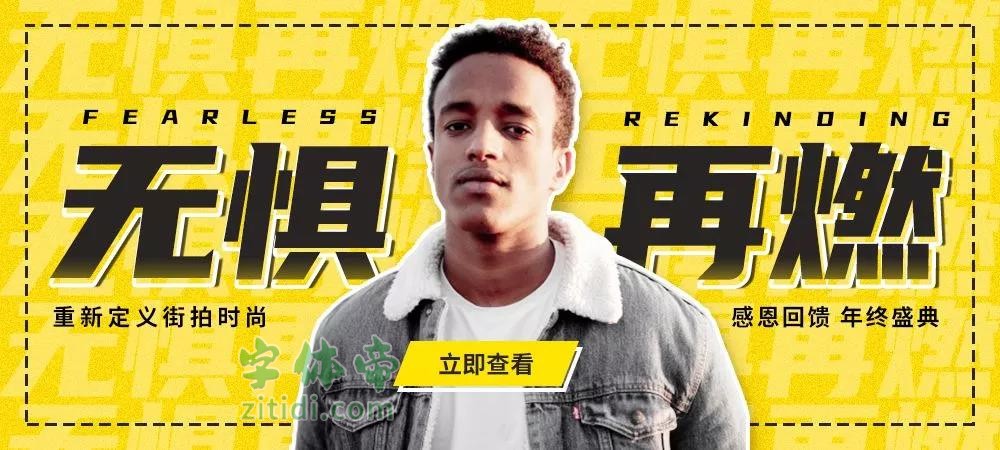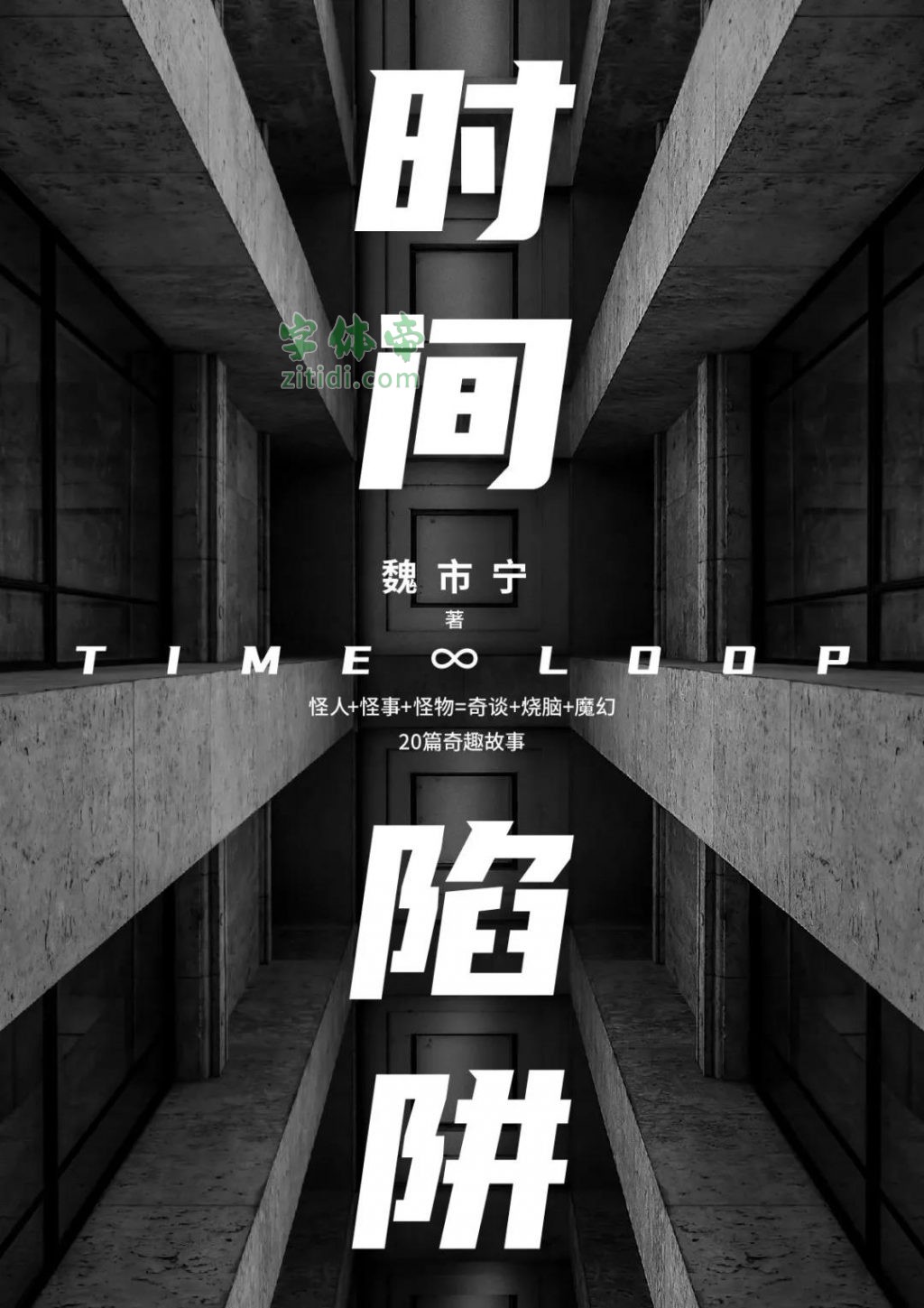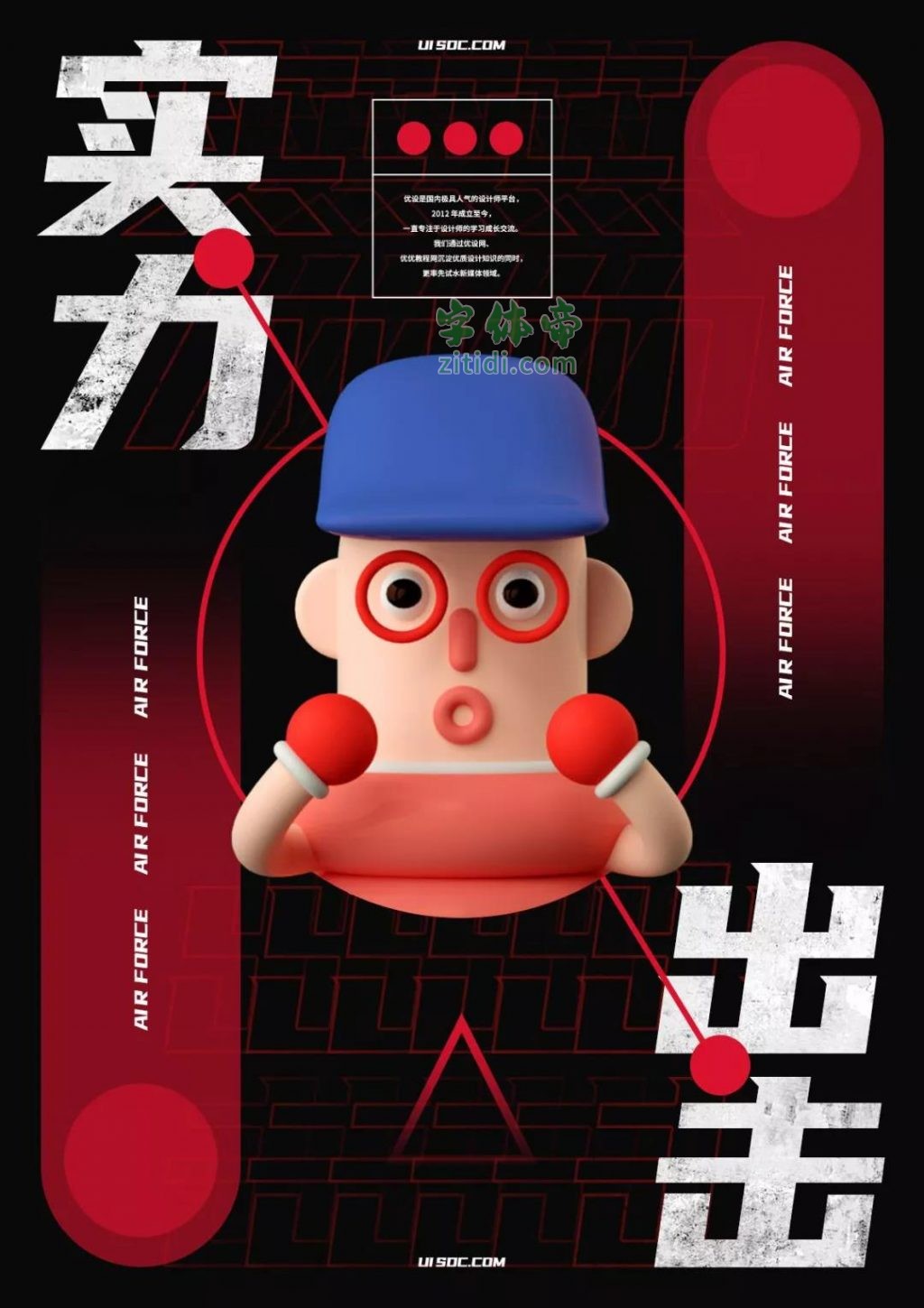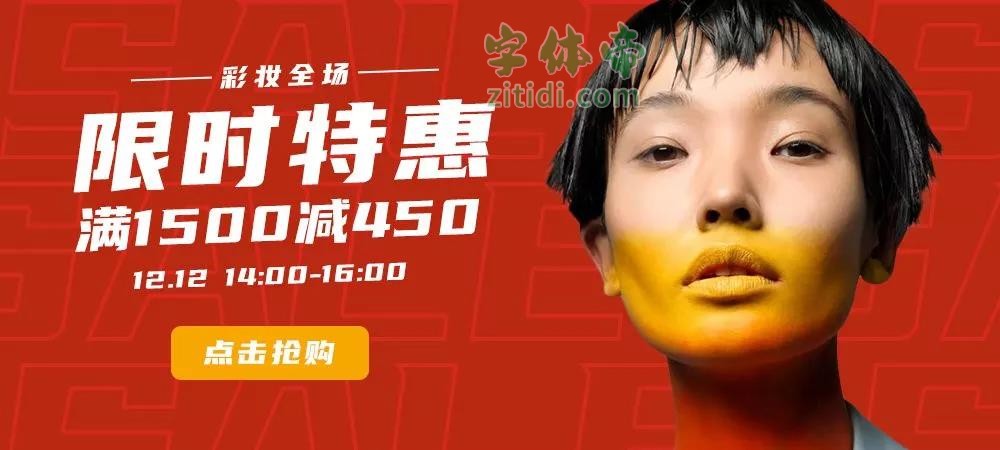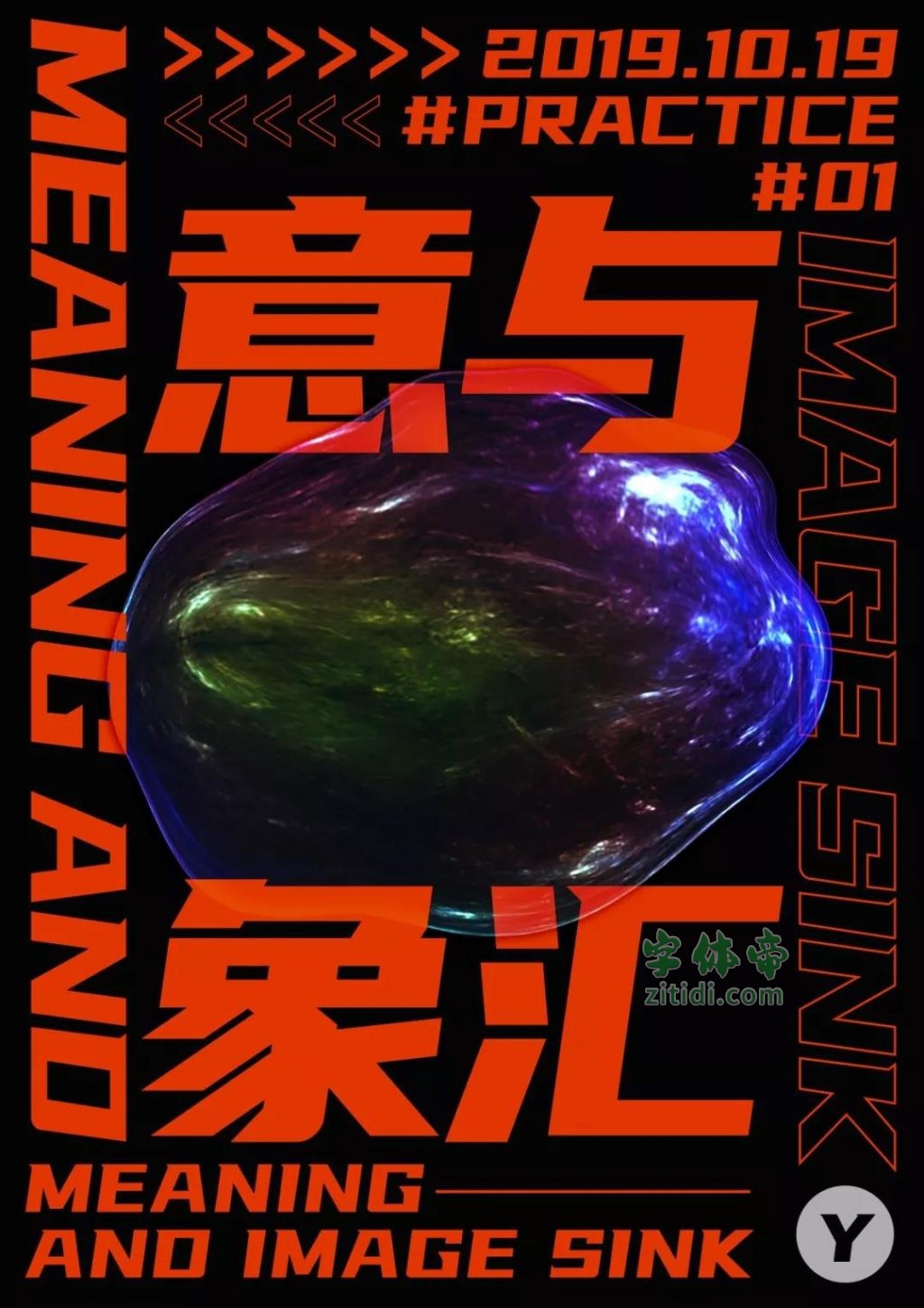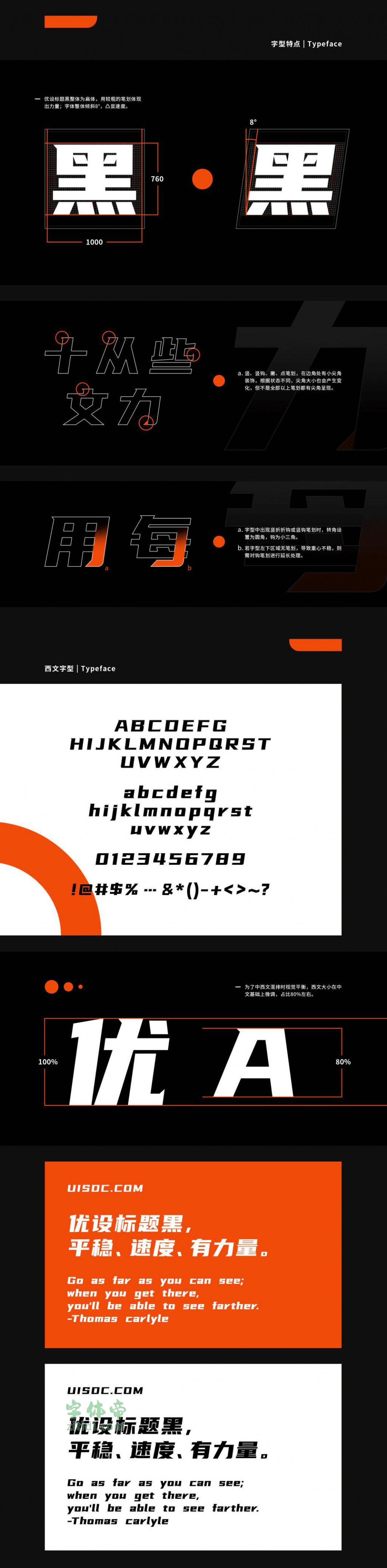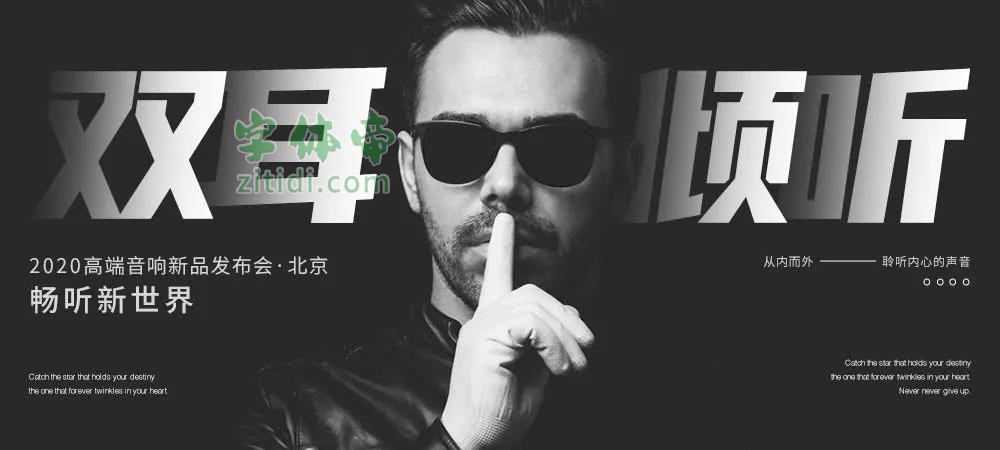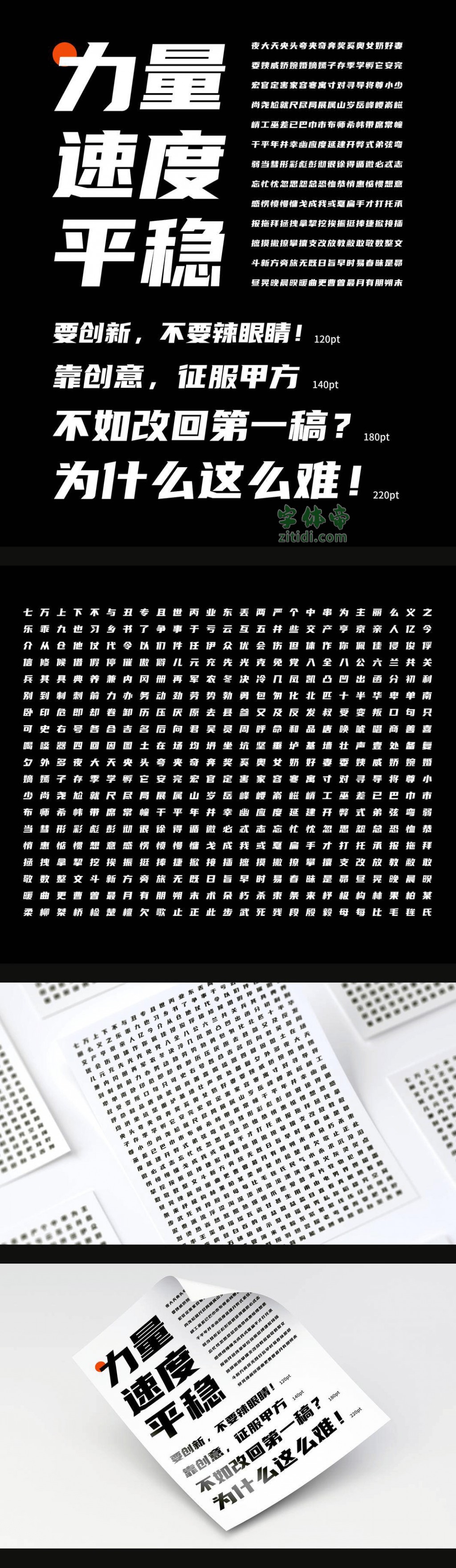
优设标题黑的设计思路来源于对目前市面上宣传物料标题用字的观察。我们发现越来越多的广告标题字体会使用这类倾斜的、粗壮的黑体字。但目前市面上这类中文字库少之又少,多数还是需要设计师自行设计。所以在优设8周年之际,为了感谢粉丝们的一路支持,优设联合字由平台共同特制这款免费可商用字体为行业献礼。
在最初有了要制作一款免费商用字体的想法时,正好遇到字由的朋友,我们一拍即合,达成了联合发布优设免费字体的共识。为了保证字体顺利快速的发布,优设邀请字由联合参与并对字体的质量把关,在优设制定完 300 多个基础字型、字母及符号的创意与规范后,字由接手继续从字库角度出发,整体完善优化字型,完成了6000多个字型的制作,并用了大量时间来进行产品化和字体细节方面的优化。
历经 100 多天,不断推翻和调整细节后,这款包括 6763 个汉字和字符的「优设标题黑」终于在优设 8 周年之际,正式上线了!
优设标题黑这款字体是一款速度感、力量感极强的专业美术标题字体。它以黑体字型为基础,加强笔画设计上的几何感。通过较大字面、精壮的笔画,强化力量感。并通过将每个字体水平倾斜8度来强化速度感。为了让字体在倾斜过后也能保持稳固,将整体字身设定宽扁。这款字体非适用在各类品牌宣传广告和产品包装设计的标题上。